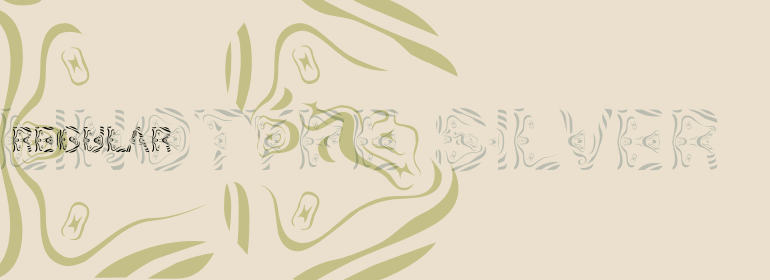
Linotype Silver™
Linotype Silver™,这款字体结构工整、笔画清晰,兼顾美观与易读性,适用于标题、正文、海报、包装、LOGO 等多种场景。字形优雅稳定,风格百搭耐看,适配日常排版与创意设计,让文字呈现更舒适、更具质感。Linotype Silver™一笔一画,皆是细节,以均衡的比例、流畅的线条打造舒适视觉体验,字形端正大气,风格简约现代。无论是商业设计、品牌宣传还是日常排版,都能轻松驾驭,让文字更有格调与力量。Linotype Silver™字体下载。
字体品牌: Linotype(Monotype) 设计师:Tomás,Jan 字体分类:衬线体 字体属性:外文 字符集:Unicode 发布时间: 2018